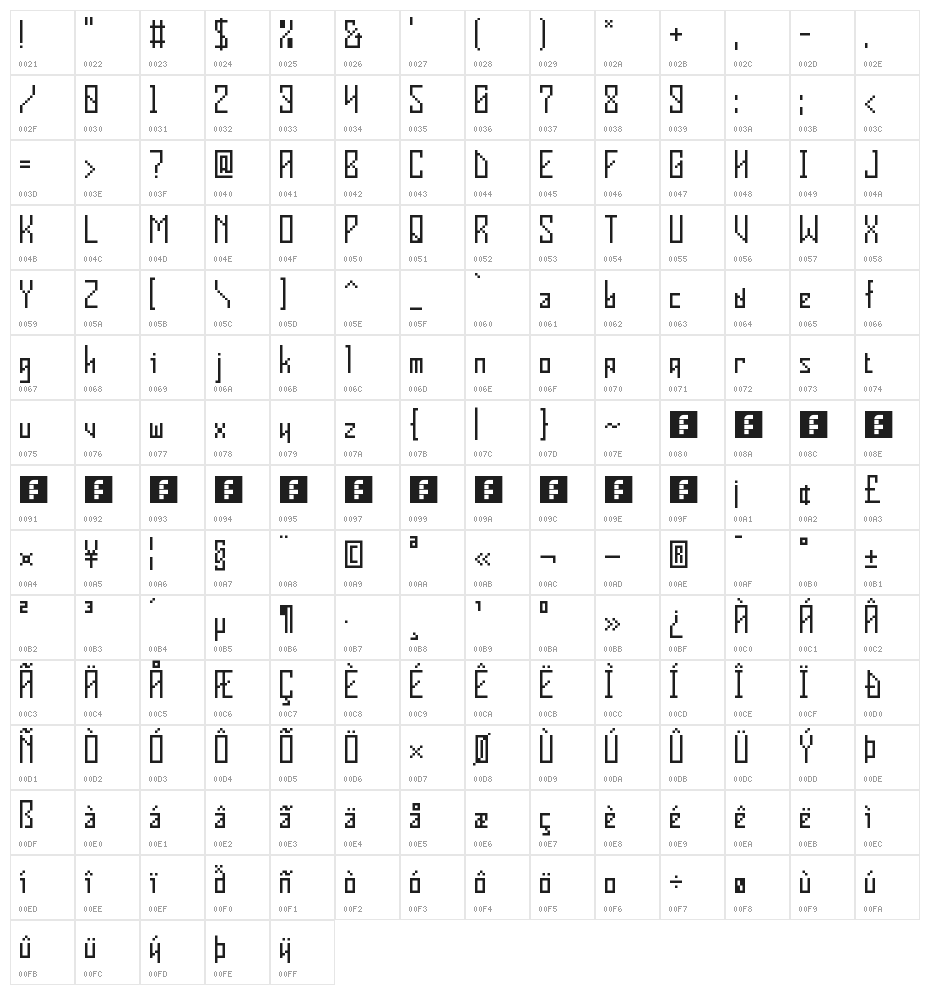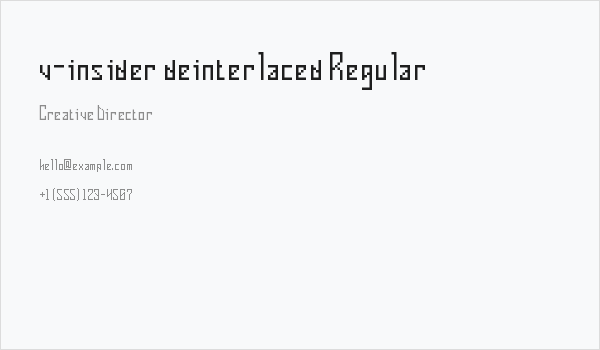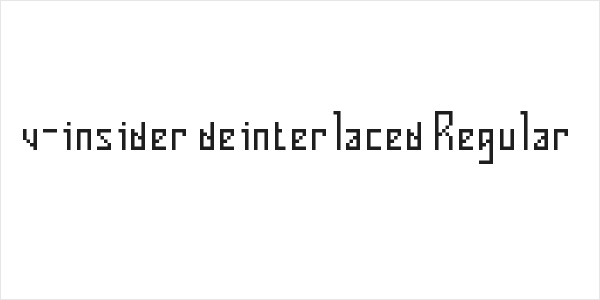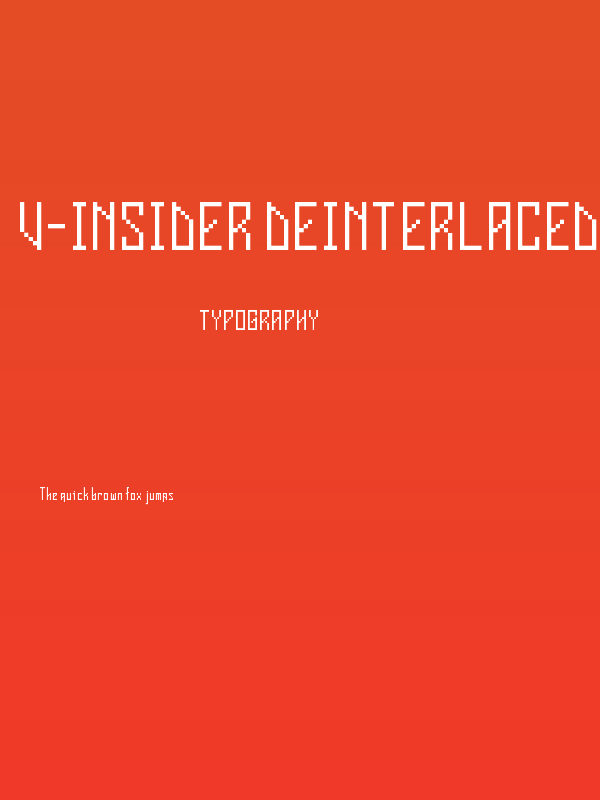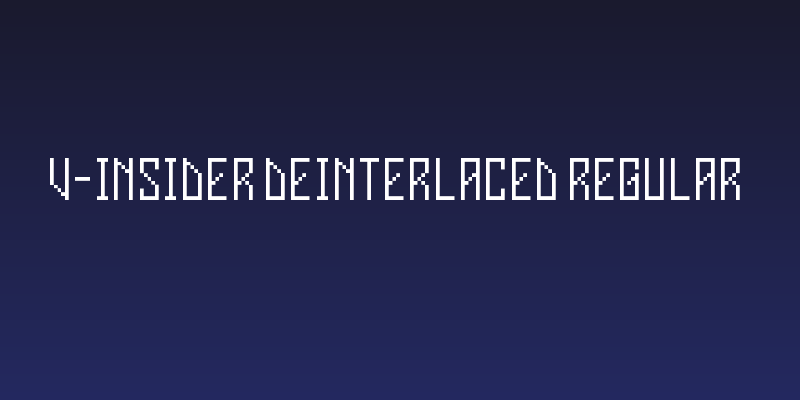
v-insider deinterlaced Regular Font
| Stile generale | Retro, Digital |
| Progetti proposti | Ideal for retro video game designs, digital art projects, tech-themed posters, and any creative work that seeks a vintage digital aesthetic. |